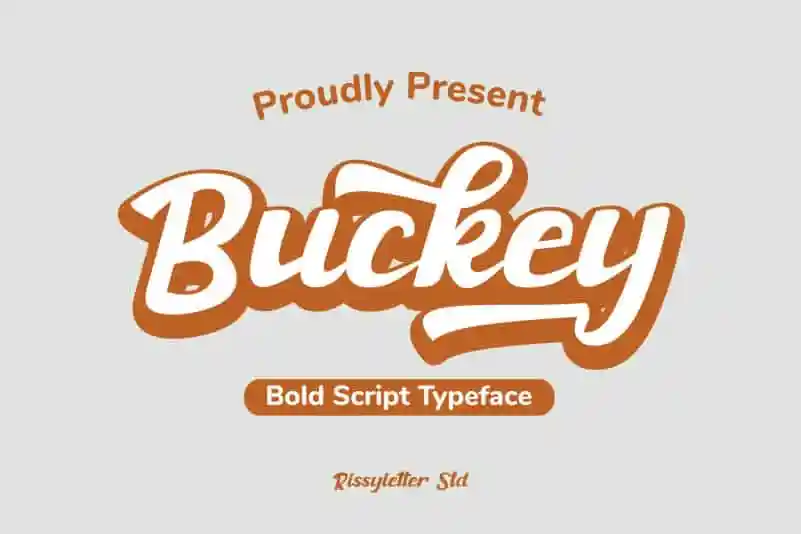
Buckey Script Font é uma fonte script estilizada com traços finos, bold e forte que exibe um impressionante enfeite elegante, clássico e único. Desenvolvida por Rissyletter Studio, esta fonte permite criar tipografia de mão-feita, encantadora e nostálgica, mantendo o aperfeiçoamento para as necessidades modernas de tipografia. Suave e versátil, ela é perfeita tanto para logotipos e identidade visual quanto para anúncios, embalagens, convites, etiquetas, ilustrações infantis, títulos de jogos e outros materiais gráficos. Com Buckey Script Font, você pode expressar a modernidade em um formato antiquado que continua relevante, tornando-a uma opção versátil para todos os tipos de projetos digitais.